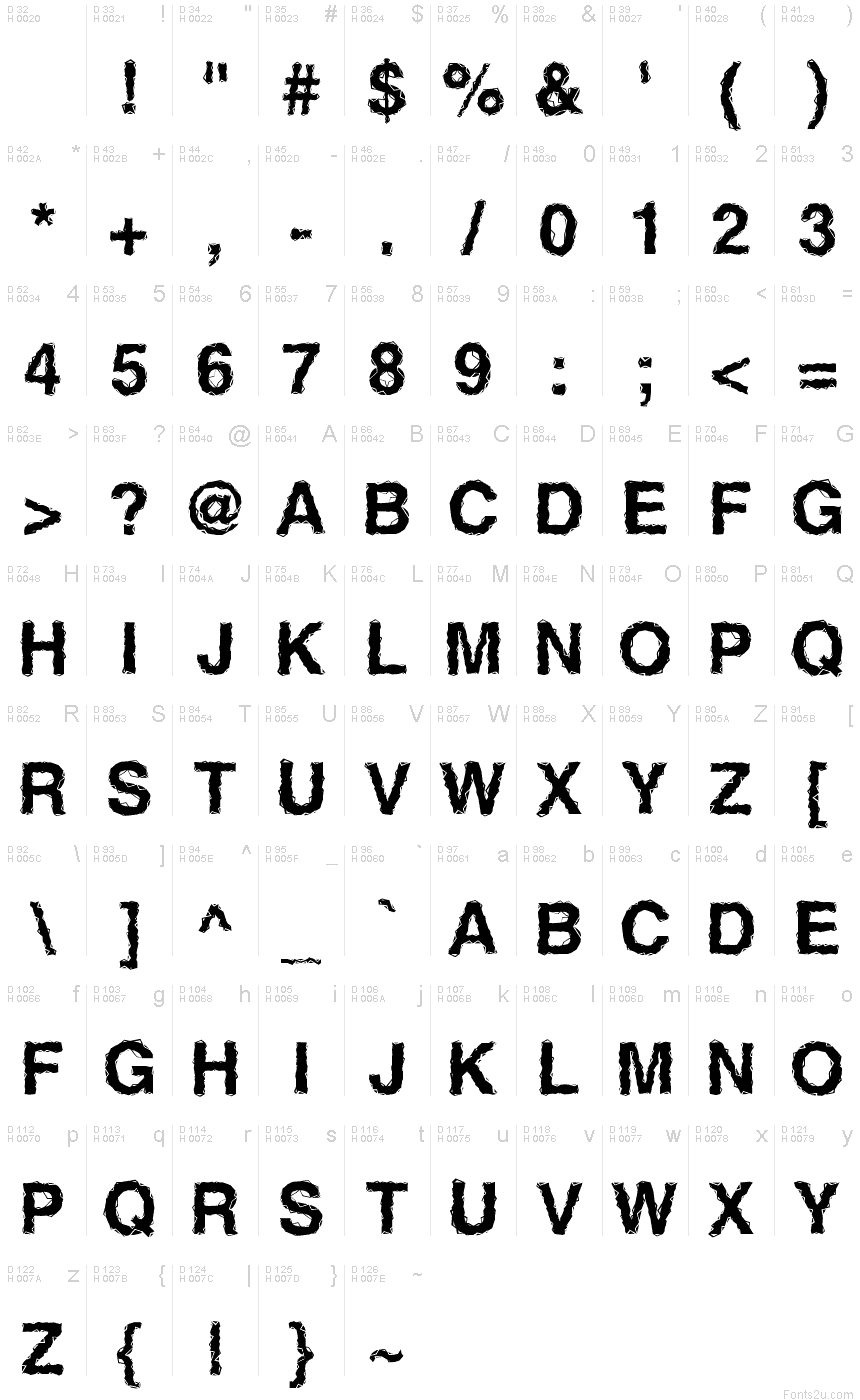
Podgląd czcionki Ben Hard Life Bold
Ben Hard Life autorstwa Bazhena Yurchenki to darmowy, zniszczony font typu display o surowym, „rozbitym” charakterze. Litery wyglądają na poszarpane i wyszczerbione na krawędziach, a masywne formy poprzecinane ostrymi wcięciami i nierównymi ubytkami nadają krojowi energię ulicznego plakatu.
Dzięki temu idealnie pasuje do muzycznych ulotek, okładek zinów, horrorowych tytułów, grafiki protestacyjnej czy logotypów gier, gdzie sterylna geometria byłaby zbyt grzeczna. Ten darmowy font najlepiej sprawdza się w krótkich, mocnych hasłach – jego poszarpane kontury i surowe kształty najlepiej działają, gdy słowa mają przestrzeń, by uderzyć z pełną siłą.